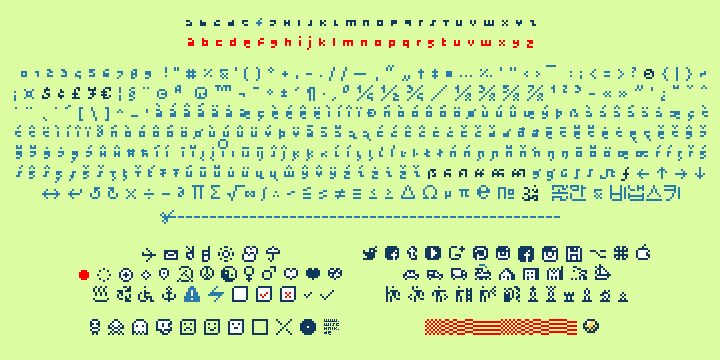
satzkorn ist eine experimentelle Pixelschrift, die ausschließlich aus Kleinbuchstaben besteht. Sie ist für eine Darstellung bei 16 Pixel Höhe optimiert, wobei sie die Optik einer 8-Pixel-Auflösung imitiert. Die "Halbpixel"-Maße dienen dabei lediglich der Optimierung des Kernings.
Satzkorn Medium
Christian Wischnewski